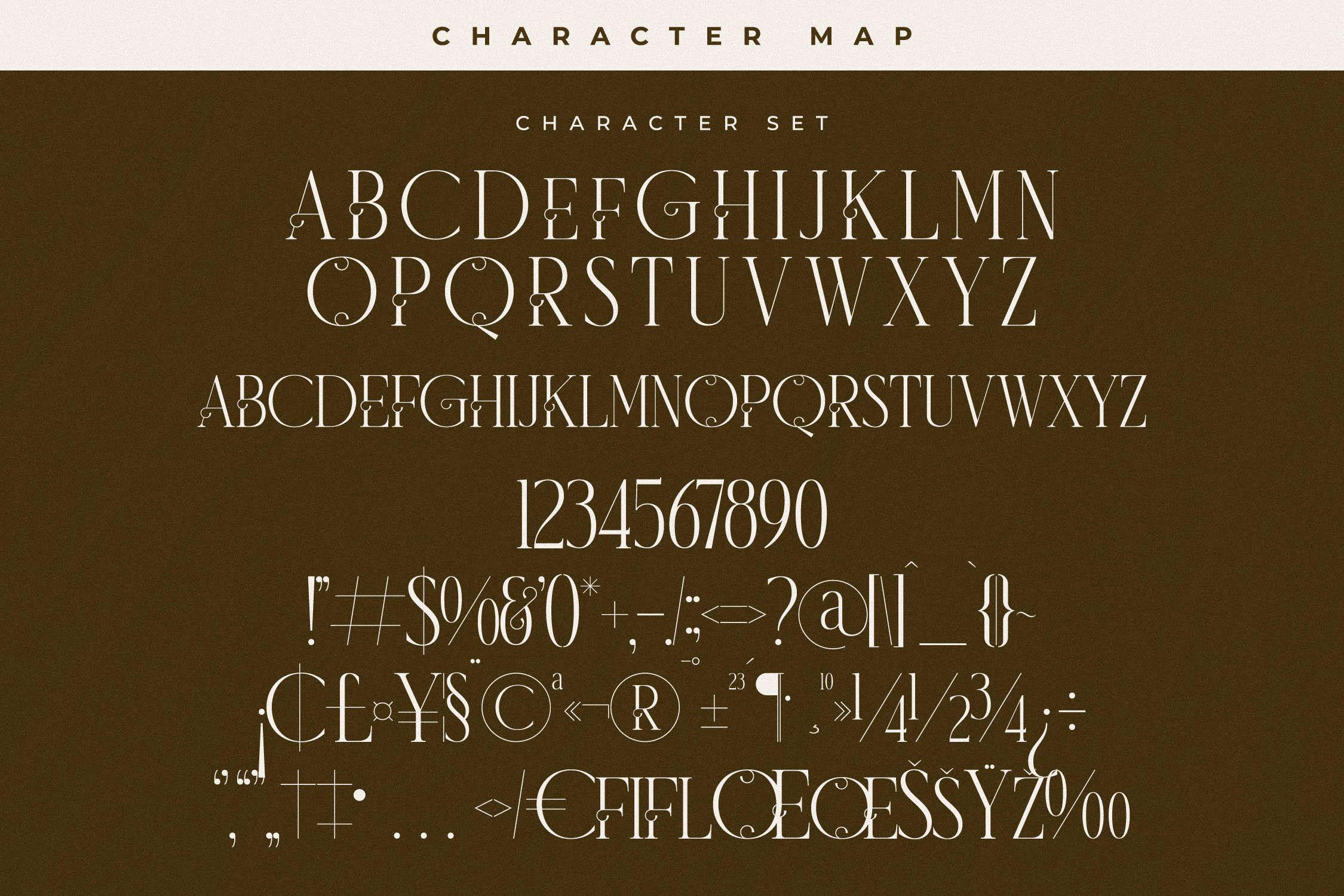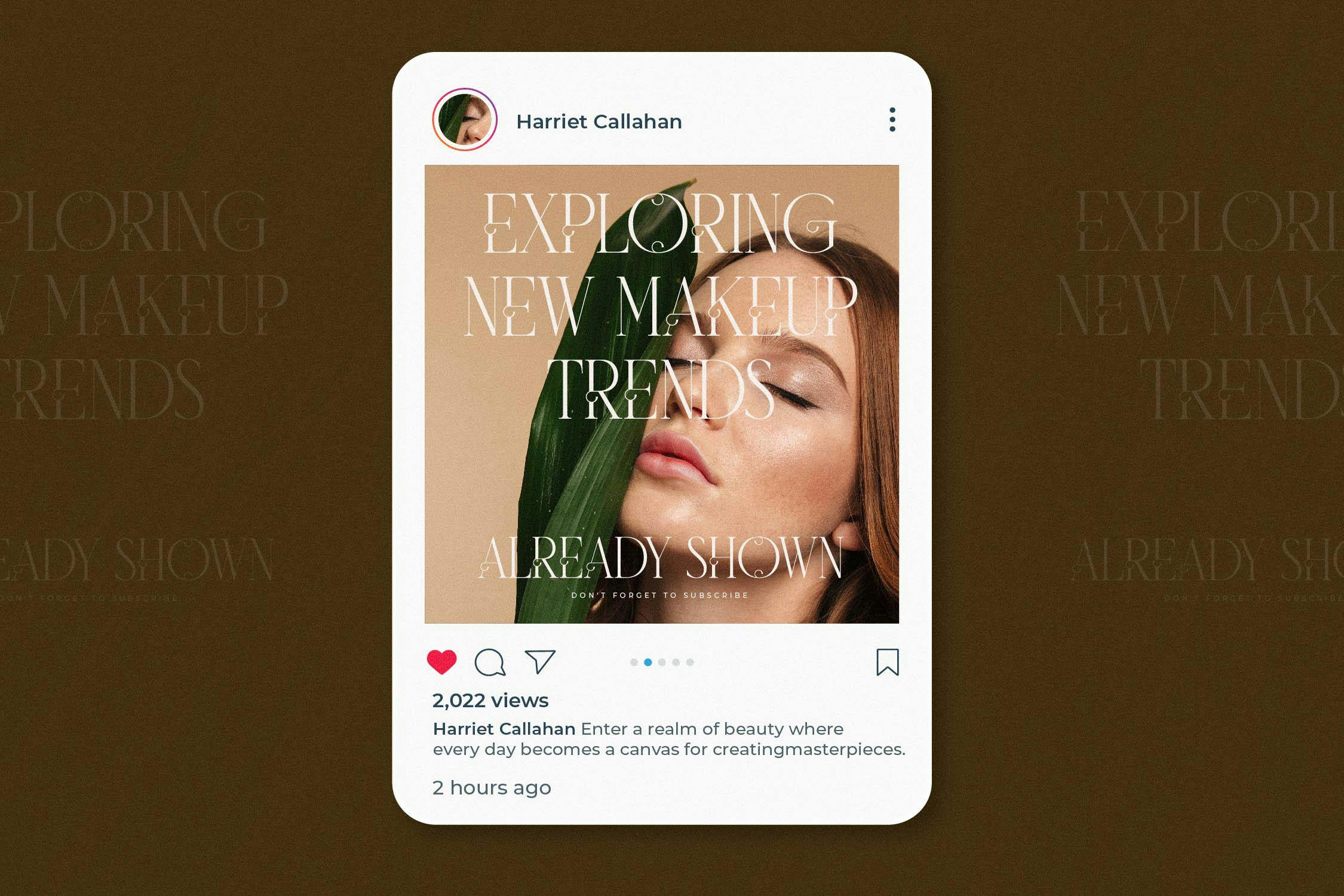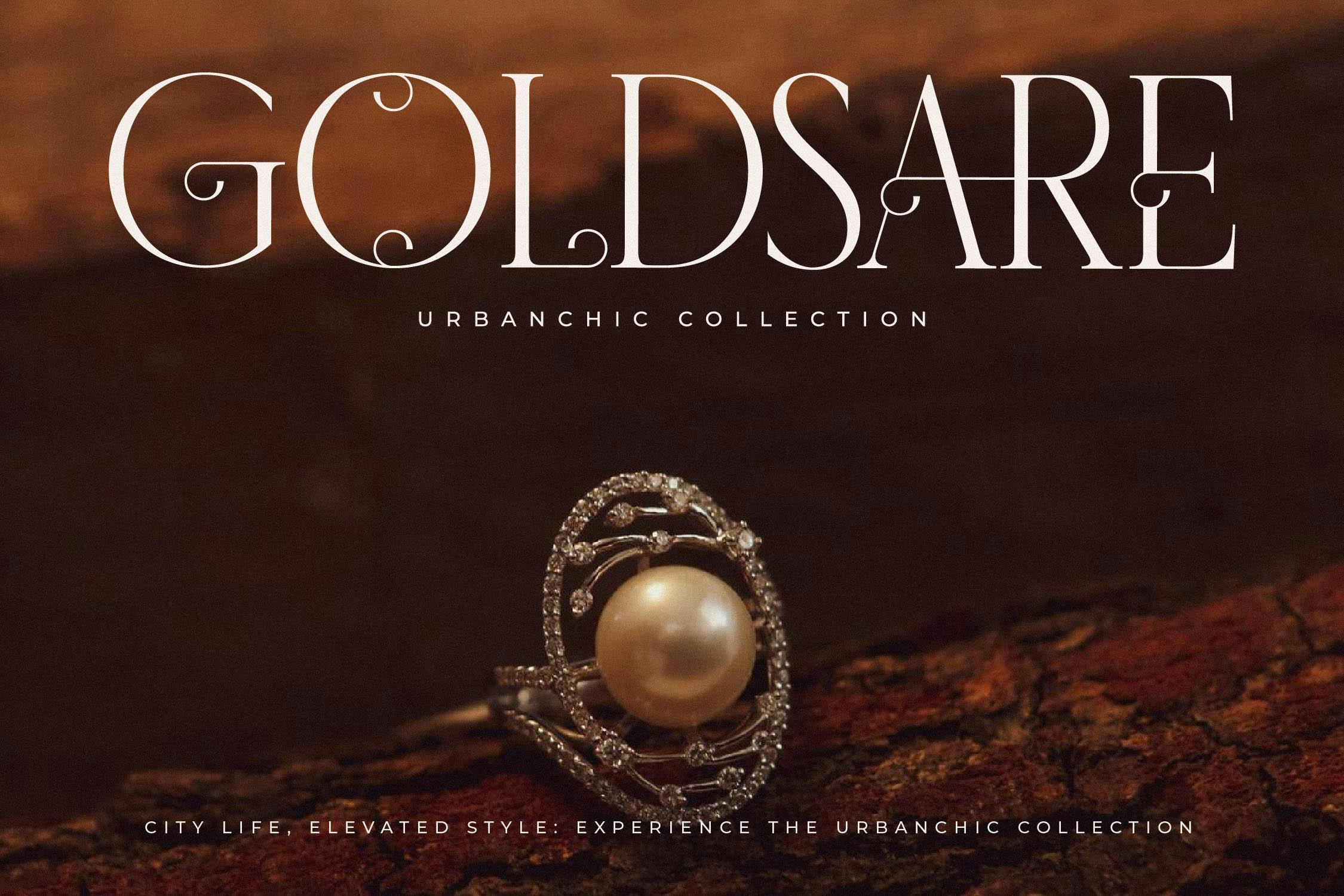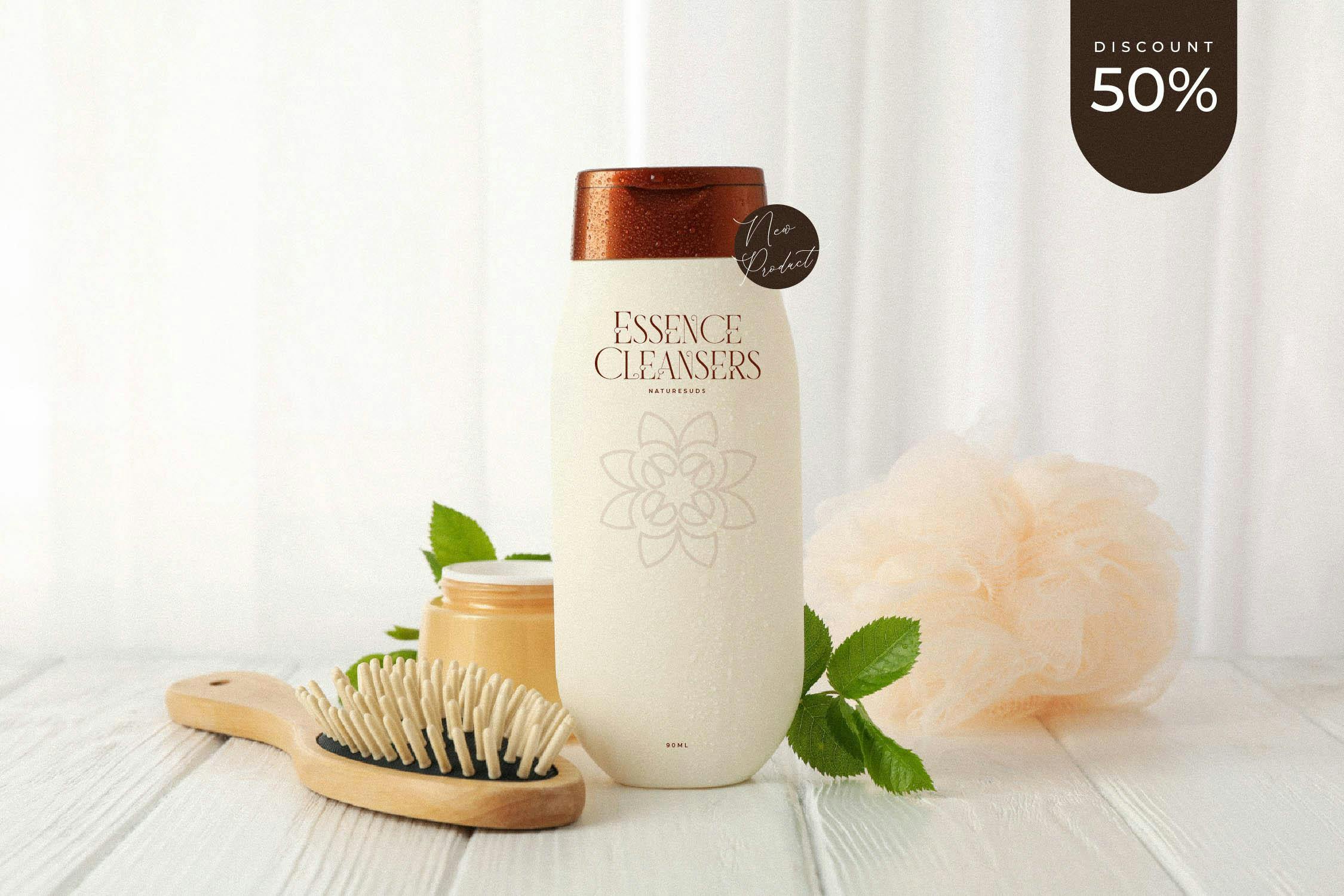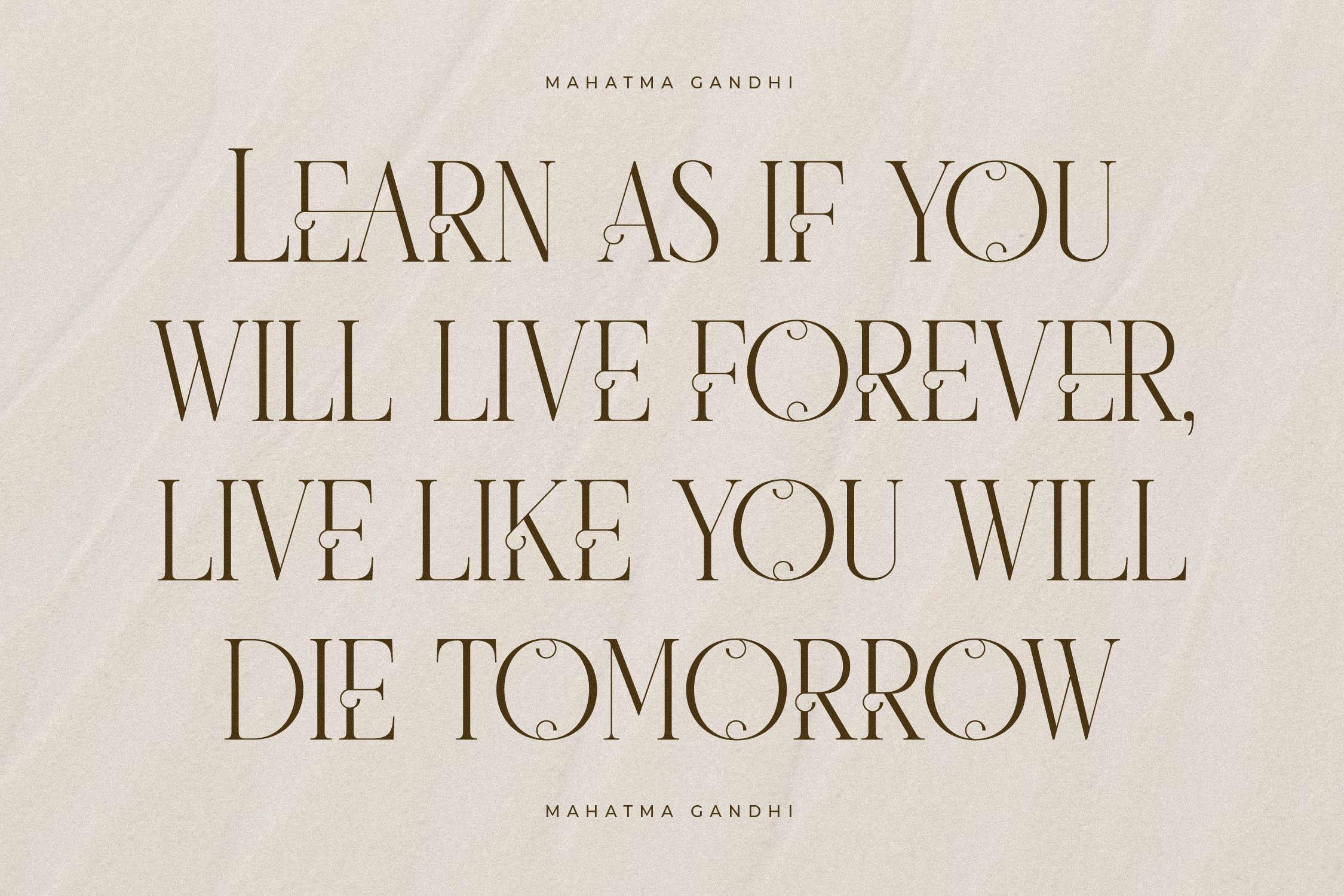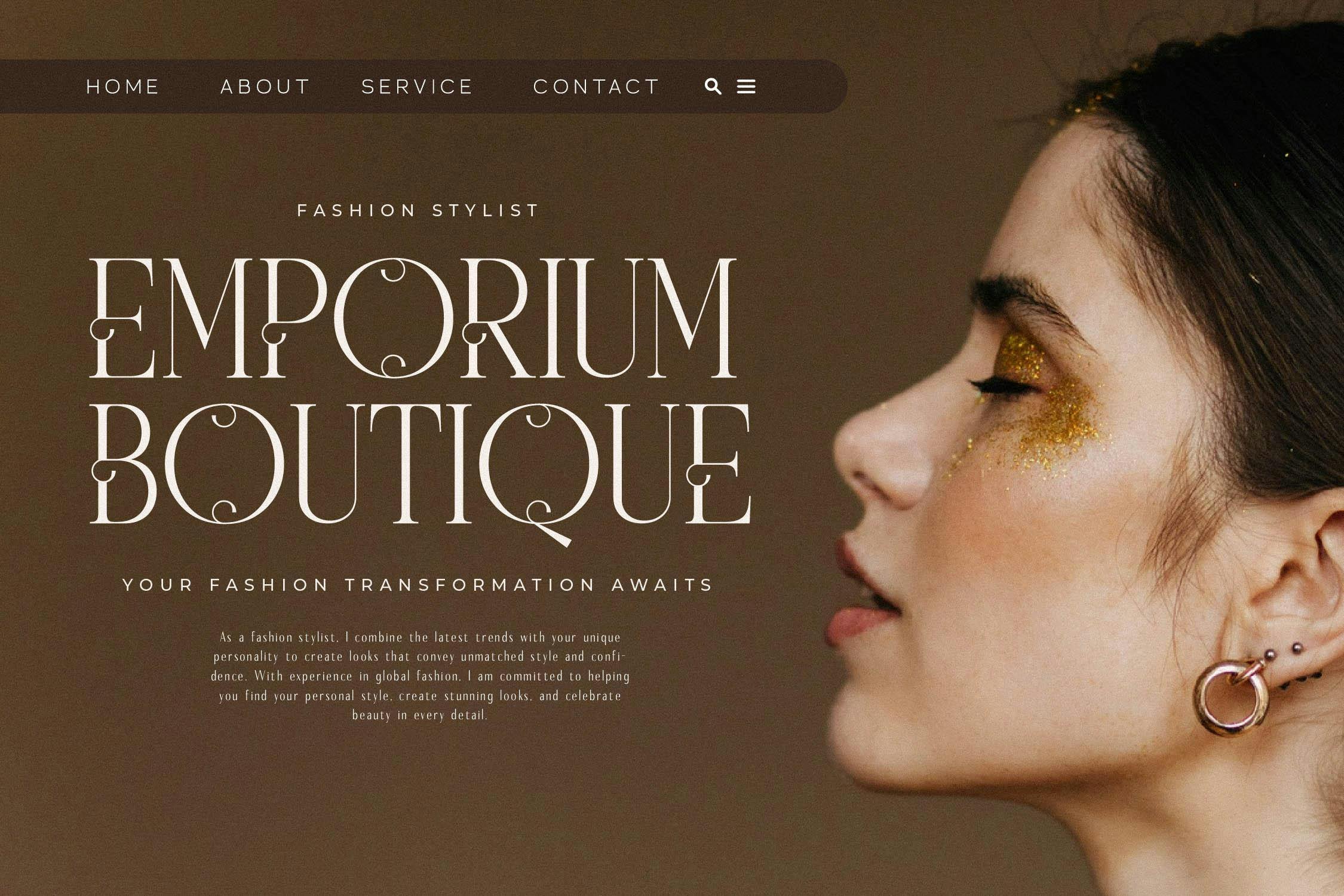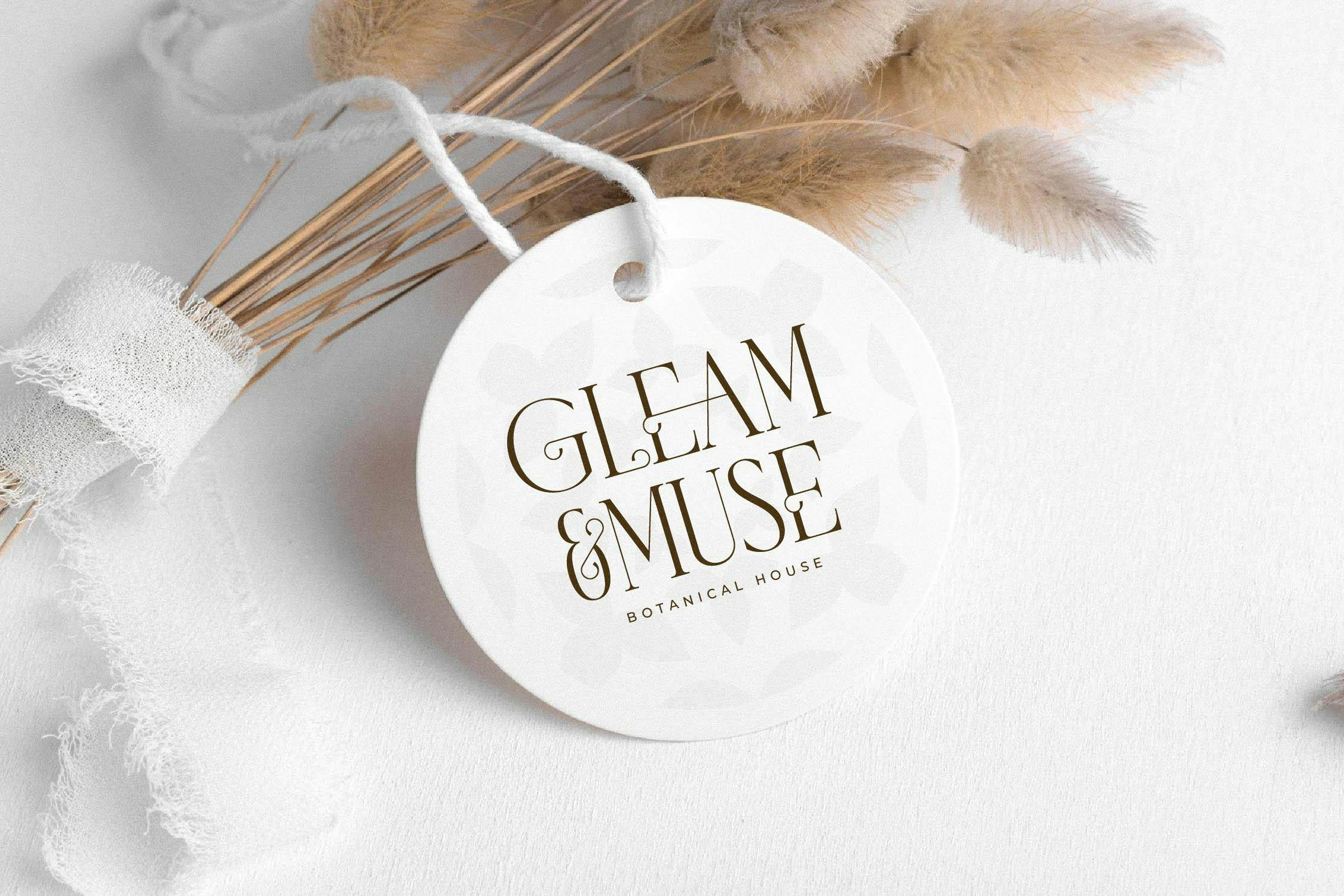
Wistern Modern Serif Font
فونت وسترن مدرن Serif مناسب برای پروژه‌های طراحی شما.
سلام خانم‌ها و آقایان، این فونت یکی از بهترین گزینه‌ها برای تکمیل محصولات خلاقانه دیجیتال و چاپی شماست. این فونت برای پوسترها، پست‌های شبکه‌های اجتماعی، برندینگ، پروژه‌های شخصی و غیره بسیار مناسب است.